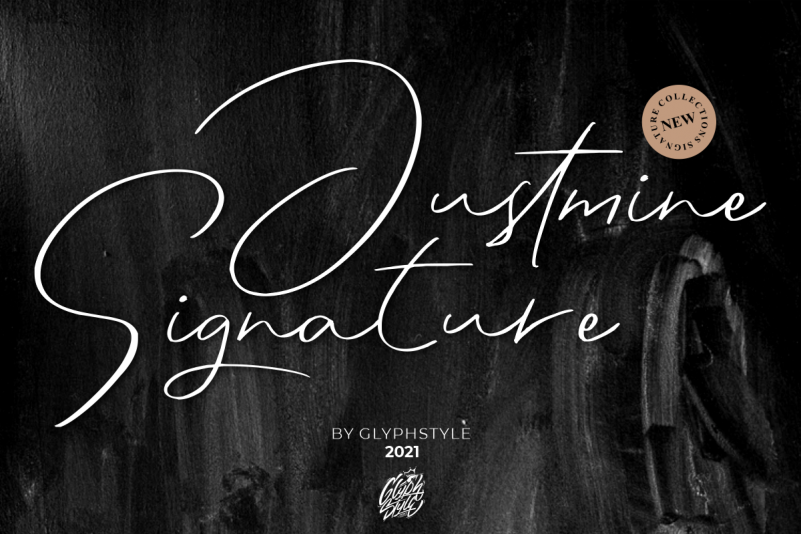
Justmine Signature Font – Download Grátis
Ajustamos a descrição para que ela seja envolvente e natural para uma página de download da fonte ‘Justmine Signature Font’, mantendo a essência original sem reproduzir literalmente: ‘Justmine Signature Font é um estilo de fonte criado para assinaturas. Especificamente projetada para ser casual e fácil de ler, esta fonte adquire o luxo e premium de que você tanto espera em elementos visuais sofisticados. Ideal para aplicações como marcas de água, identificação de marca, criação de negócios, cartões de visita, logotipos de produtos, e muito mais. Com seu charme handwritten, Justmine Signature é perfeitamente adaptável a qualquer aplicação que exige uma aparência elegante e atemporal. Seja você um designer gráfico ou um empreendedor ambicioso, esta fonte irá garantir que o seu trabalho prima por elegância e originalidade.’